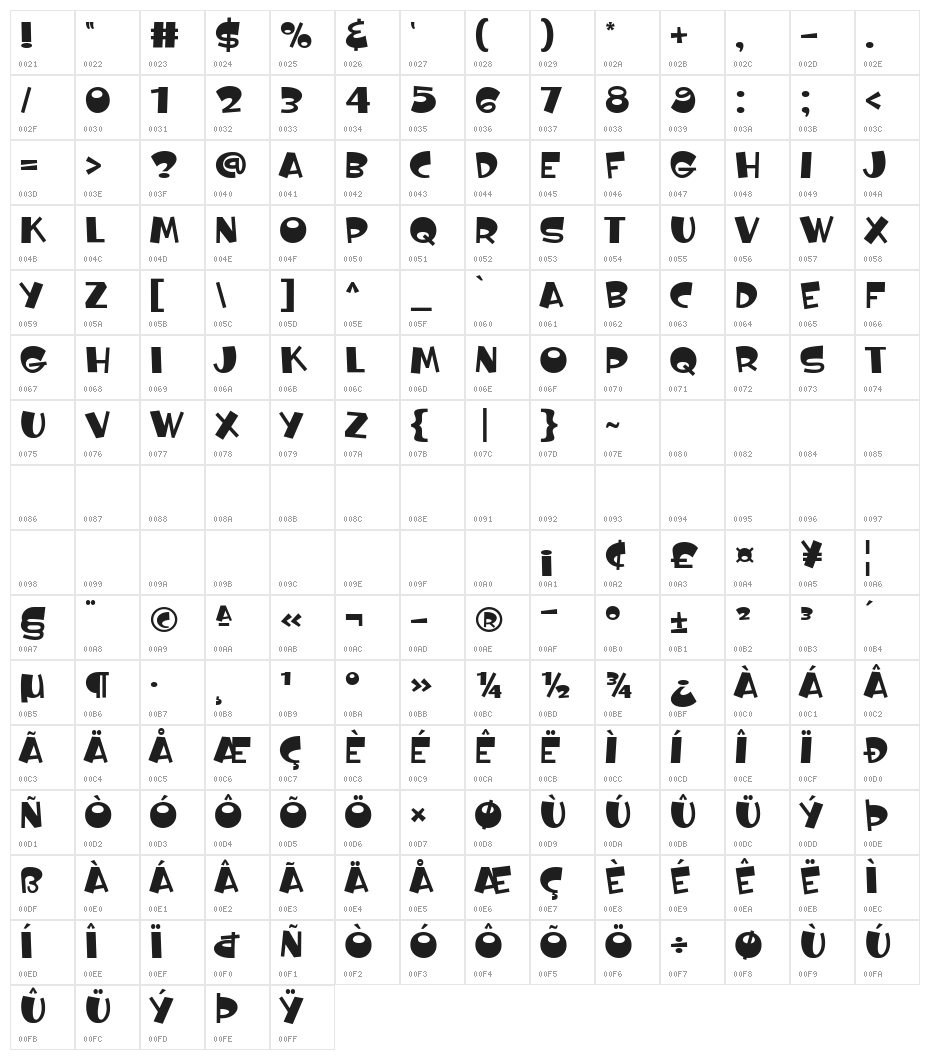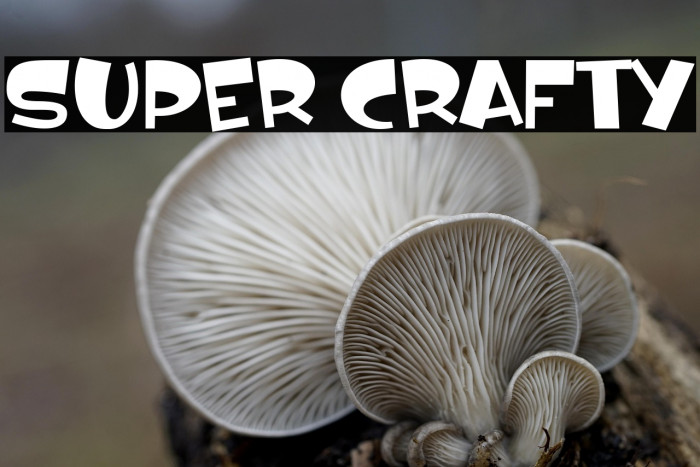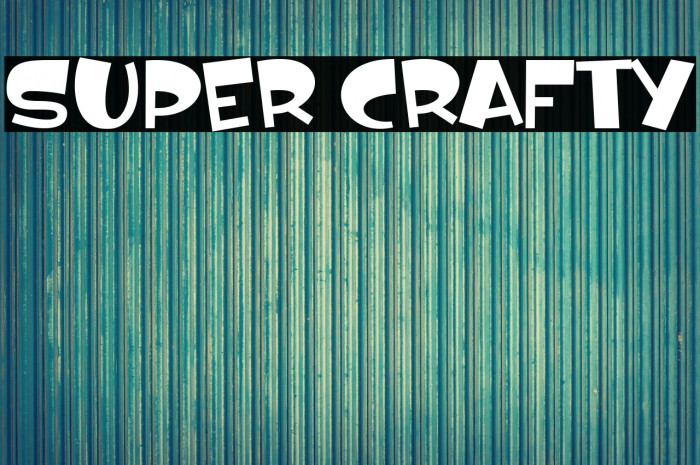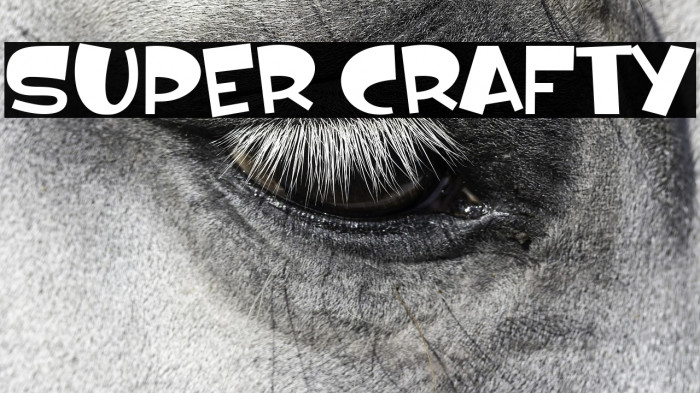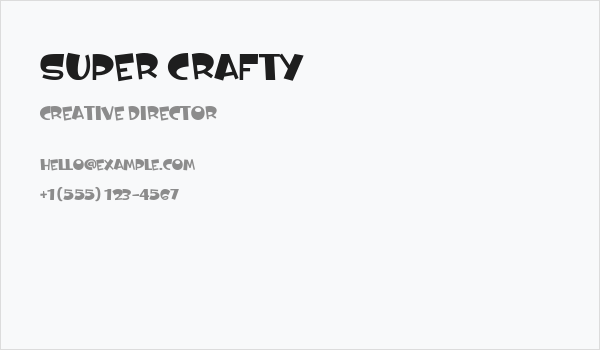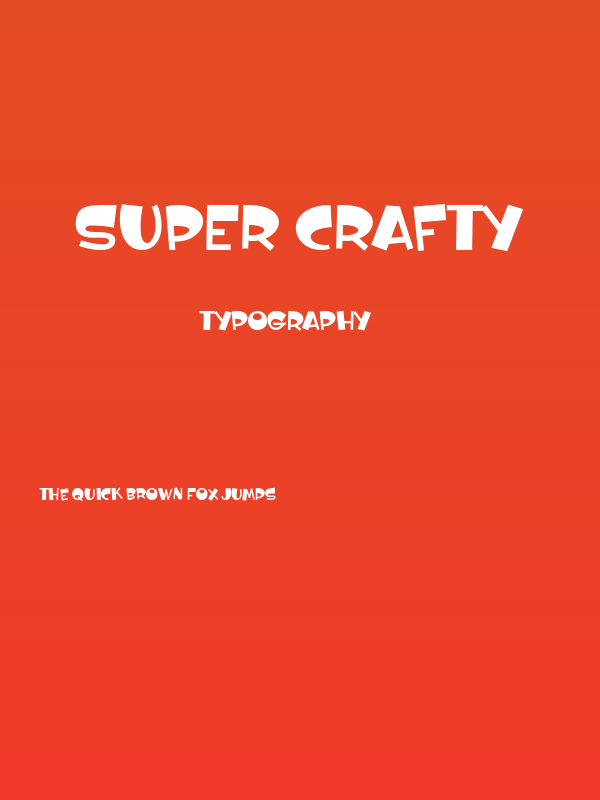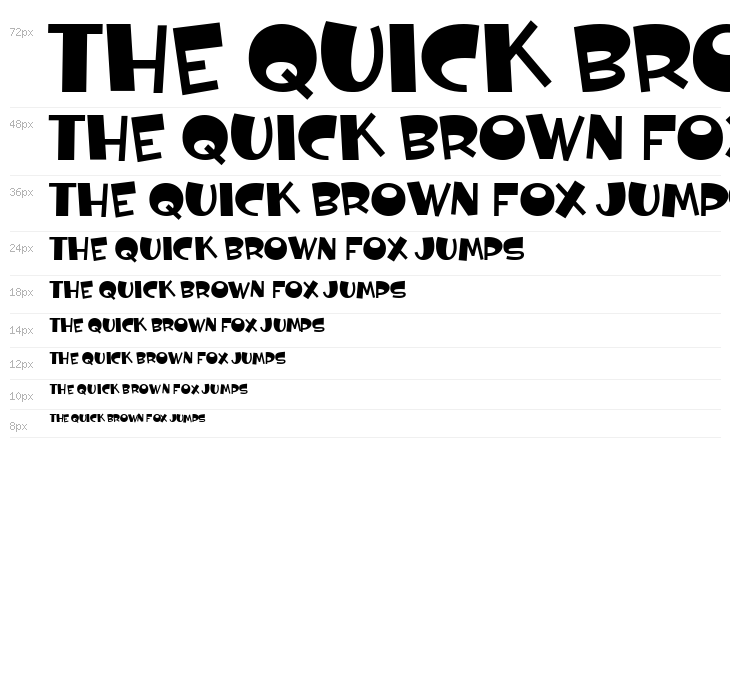
Super Crafty Font
| Stile generale | Playful, Whimsical |
| Caso d'uso | Headlines, Posters, Branding |
| Progetti proposti | Ideal for children's books, playful branding, event posters, and creative projects that require a fun and engaging typeface. |